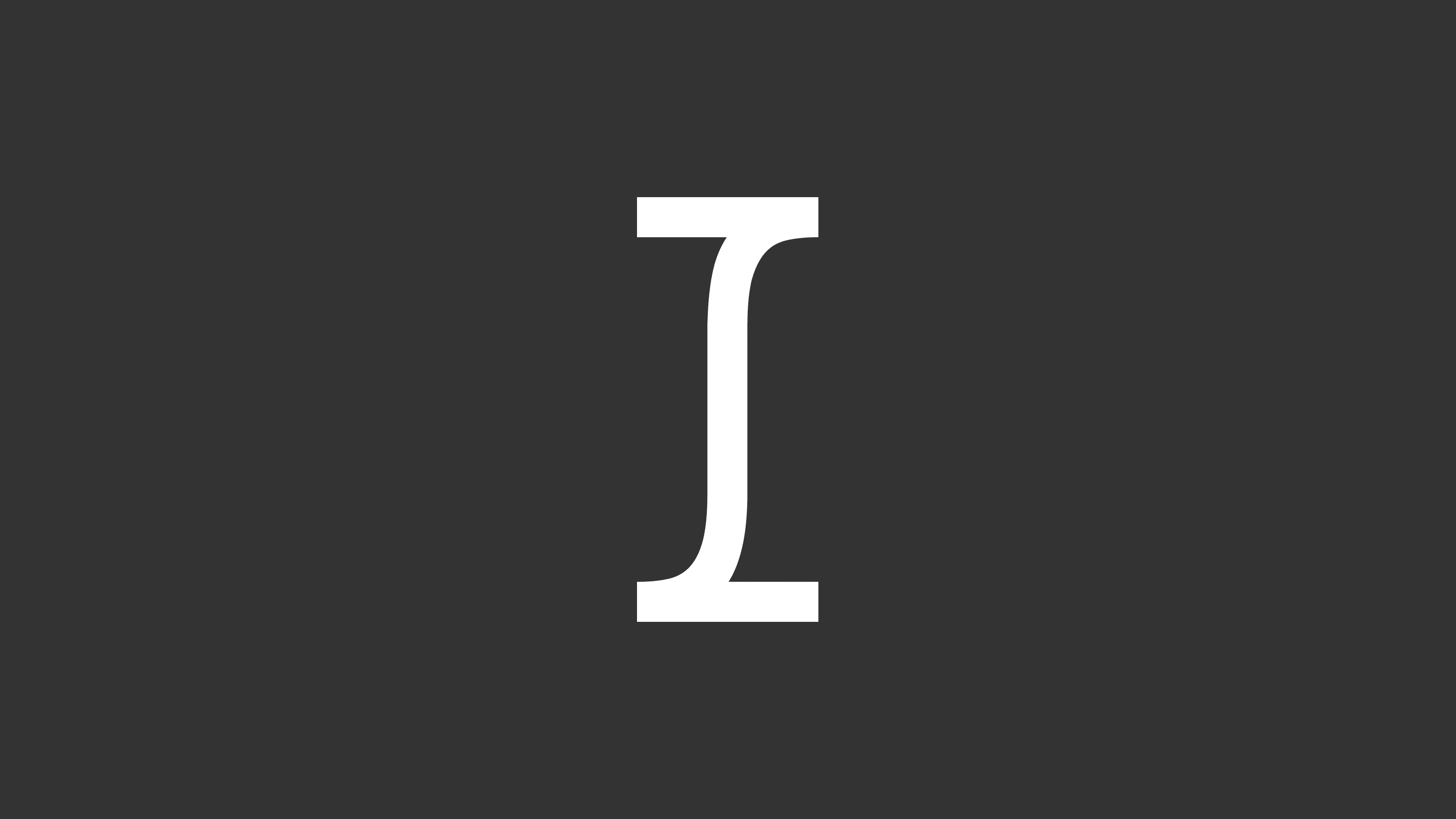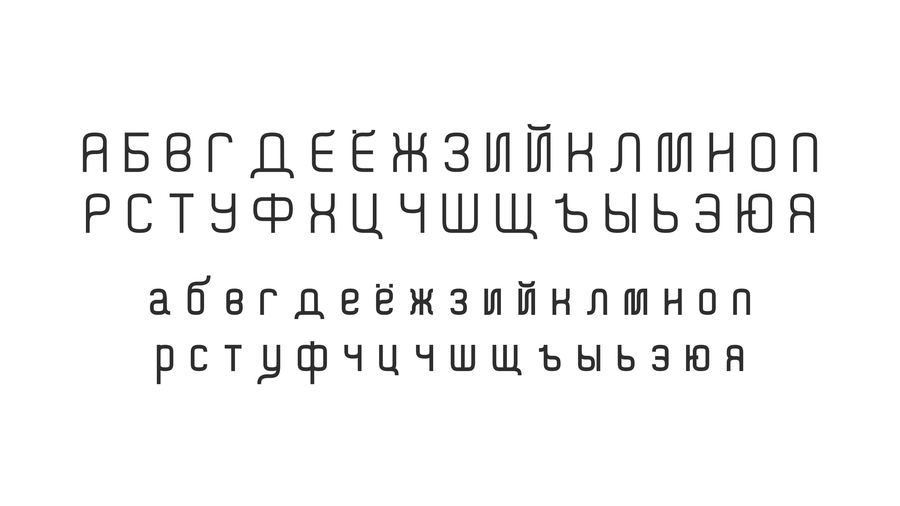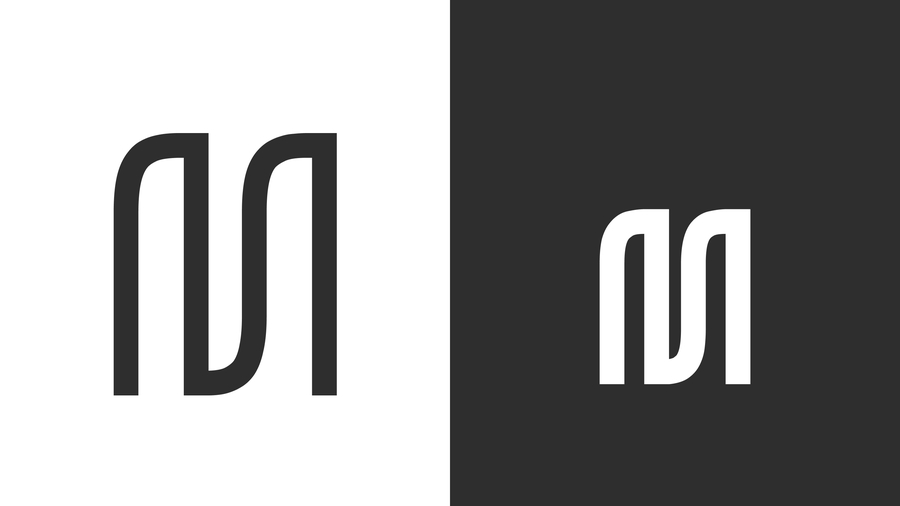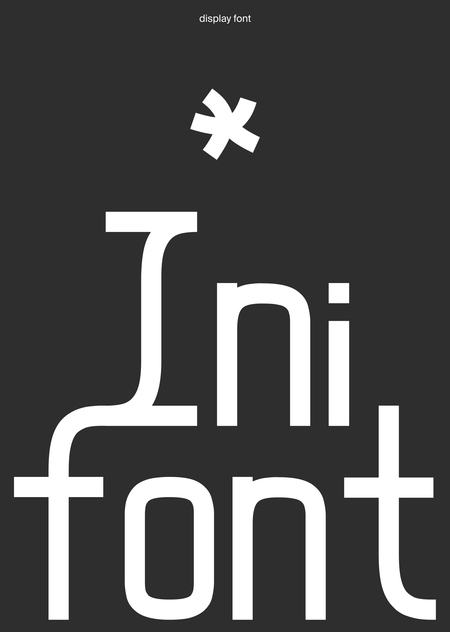
ini font — акциденция, вдохновленная армянской системой письменности
[ini] — одиннадцатая буква армянского алфавита, ее форма легла в основу пластики шрифта
кириллица
латиница
цифры и знаки